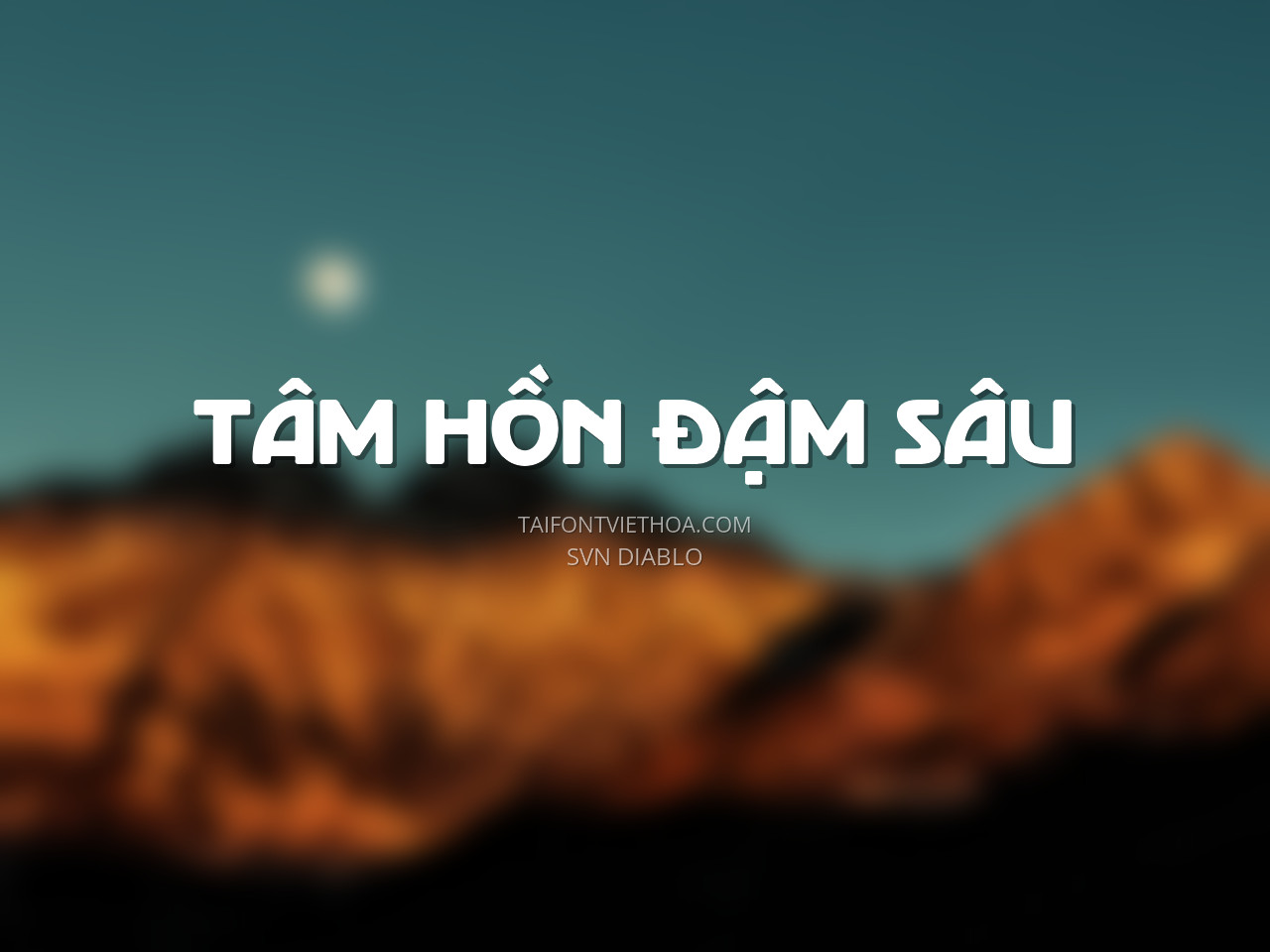
Giới thiệu về font SVN Diablo – Kiểu chữ sans-serif đậm nét, mạnh mẽ và cá tính
SVN Diablo là phiên bản Việt hóa của font Diablo – một kiểu chữ sans-serif mang phong cách đậm nét, mạnh mẽ và rất cá tính. Font được thiết kế với các đường nét sắc sảo, góc cạnh và chắc chắn, phù hợp cho các dự án thiết kế thương hiệu, quảng cáo và truyền thông kỹ thuật số.
Phiên bản Việt hóa của SVN Diablo đã được Taifontviethoa.comchăm sóc kỹ lưỡng, hỗ trợ đầy đủ dấu tiếng Việt cùng hơn 70 ngôn ngữ khác. Font giúp các nhà thiết kế dễ dàng ứng dụng trong nhiều dự án đa dạng mà vẫn giữ được phong cách mạnh mẽ, hiện đại và chuyên nghiệp.
Thiết kế sans-serif đậm nét – Ứng dụng đa dạng trong thương hiệu và quảng cáo
SVN Diablo sở hữu các nét chữ dày, sắc nét với các góc cạnh được chăm chút tỉ mỉ, tạo cảm giác nổi bật và thu hút. Font rất phù hợp cho tiêu đề, banner, logo hoặc poster cần sự ấn tượng và cá tính mạnh mẽ. Phong cách thiết kế của Diablo rất thích hợp với các dự án công nghệ, thể thao, quảng cáo và thương hiệu trẻ trung, năng động.